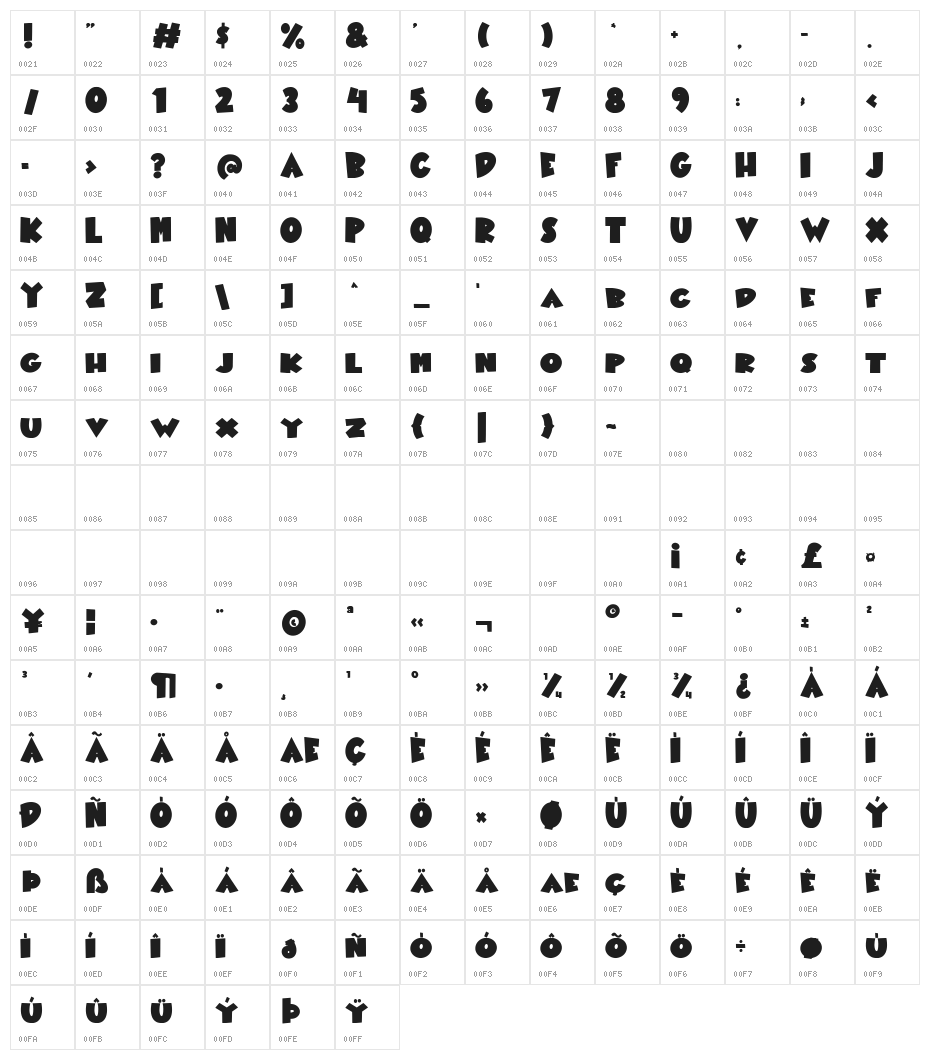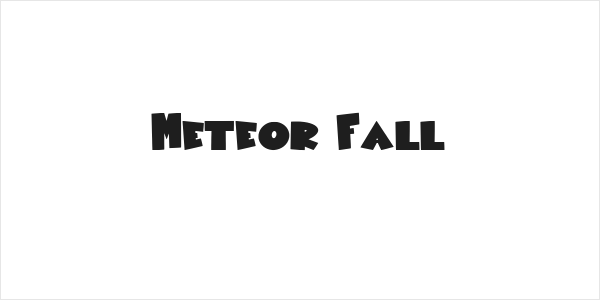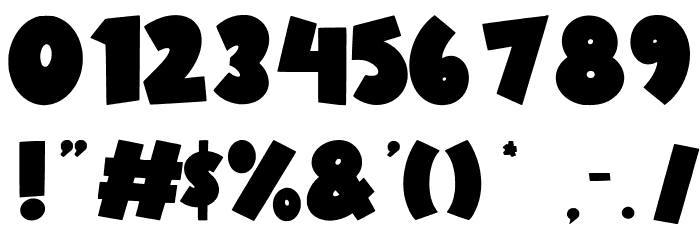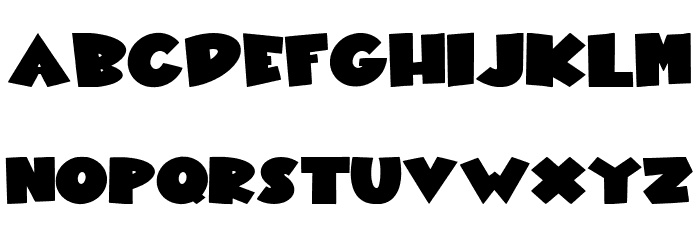
Meteor Fall Font
| النمط العام | Playful, Energetic |
| حالة الاستخدام | Headlines, Posters, Branding |
| مشاريع مقترحة | Ideal for children's books, playful branding, event posters, and any project needing a fun, eye-catching typeface. |